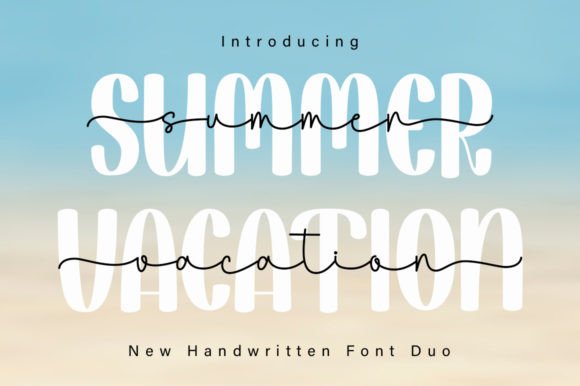
Summer Vacation Duo
Summer Vacation Duoのような高品質の素材をお探しの場合、このプレミアムパッケージはクリエイティブなプロジェクトに素晴らしい選択です。
POD(オンデマンド印刷)製品、結婚式の招待状、またはソーシャルメディアのグラフィックを作成している場合でも、Summer Vacation Duoは理想的です。